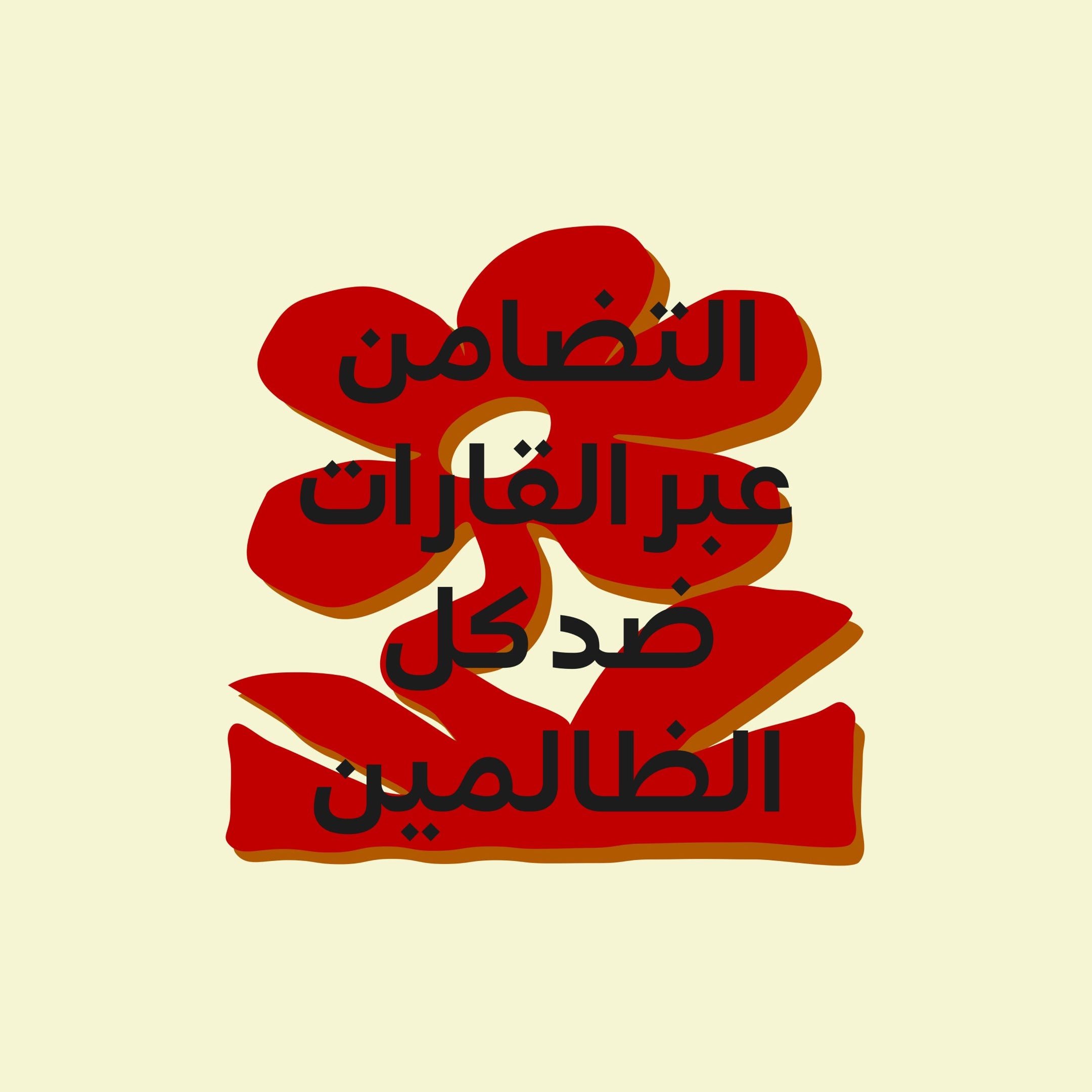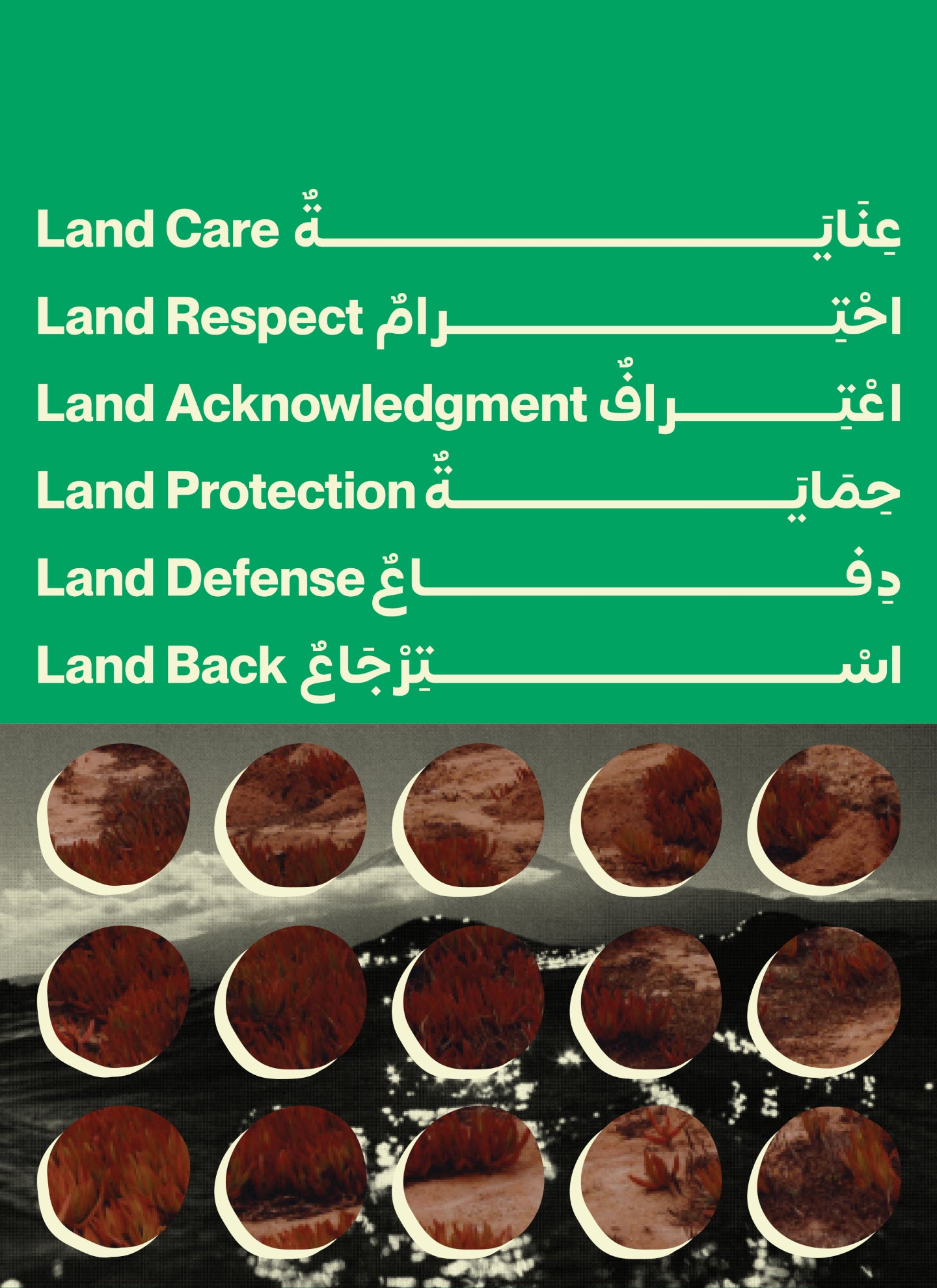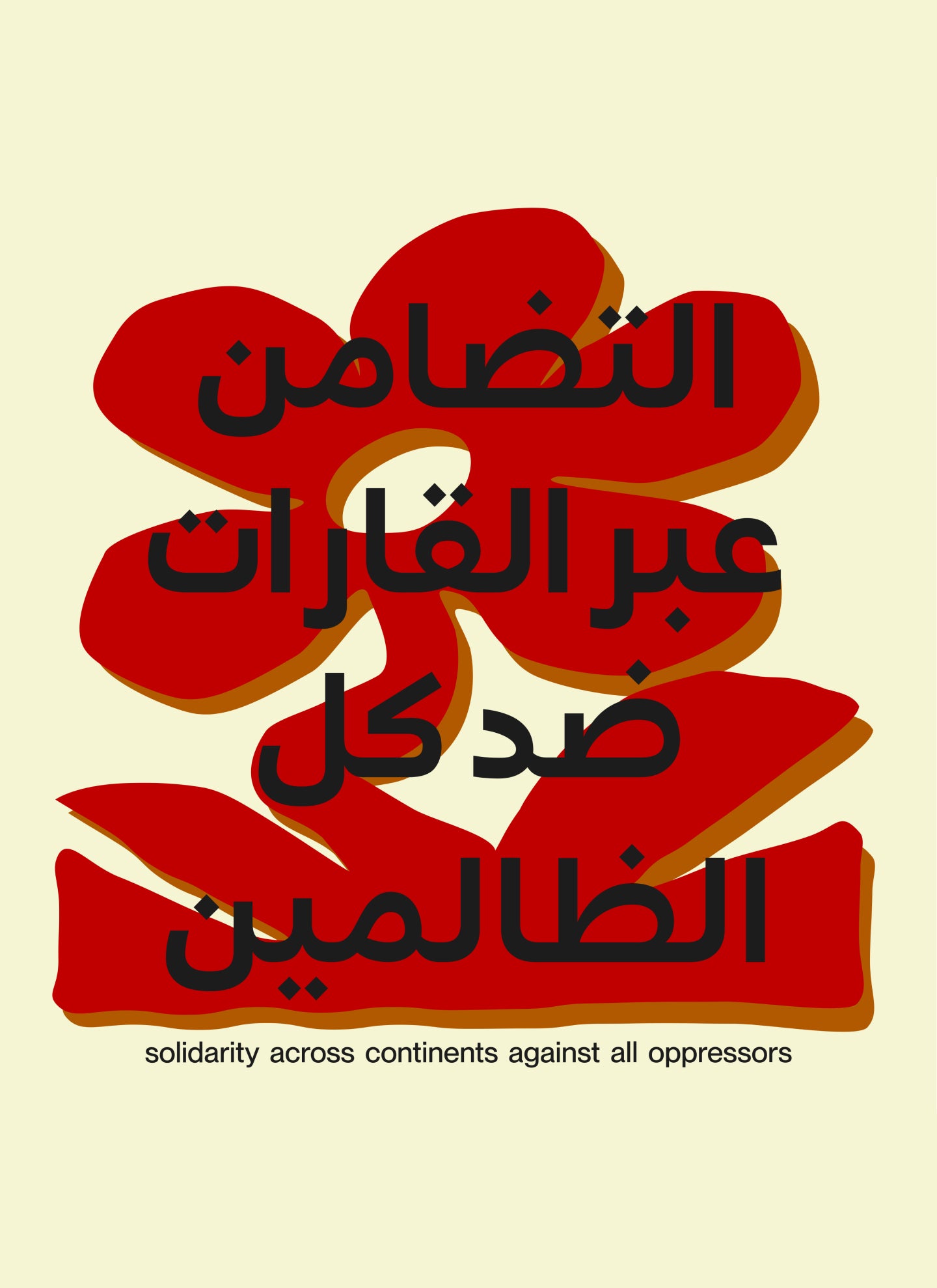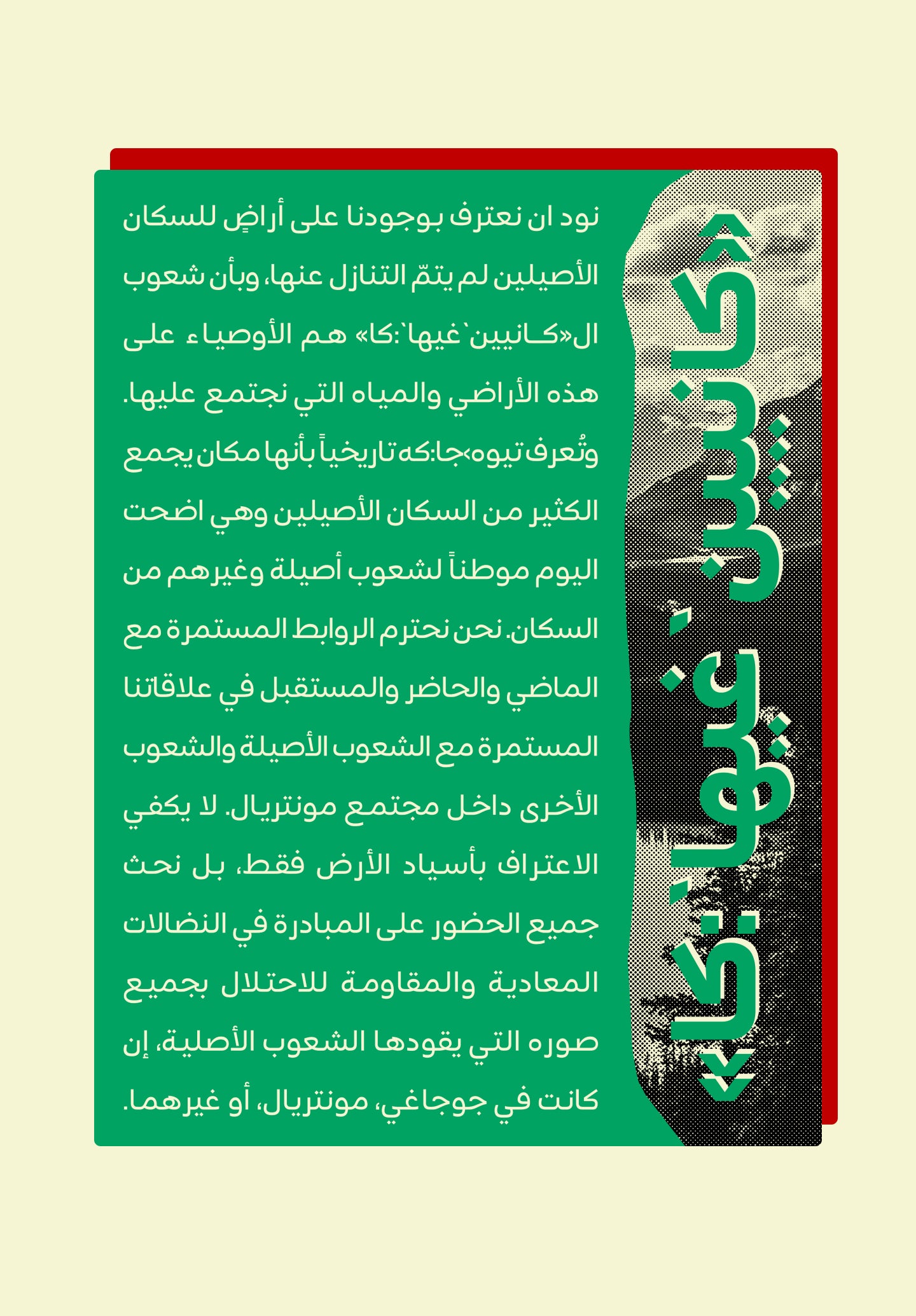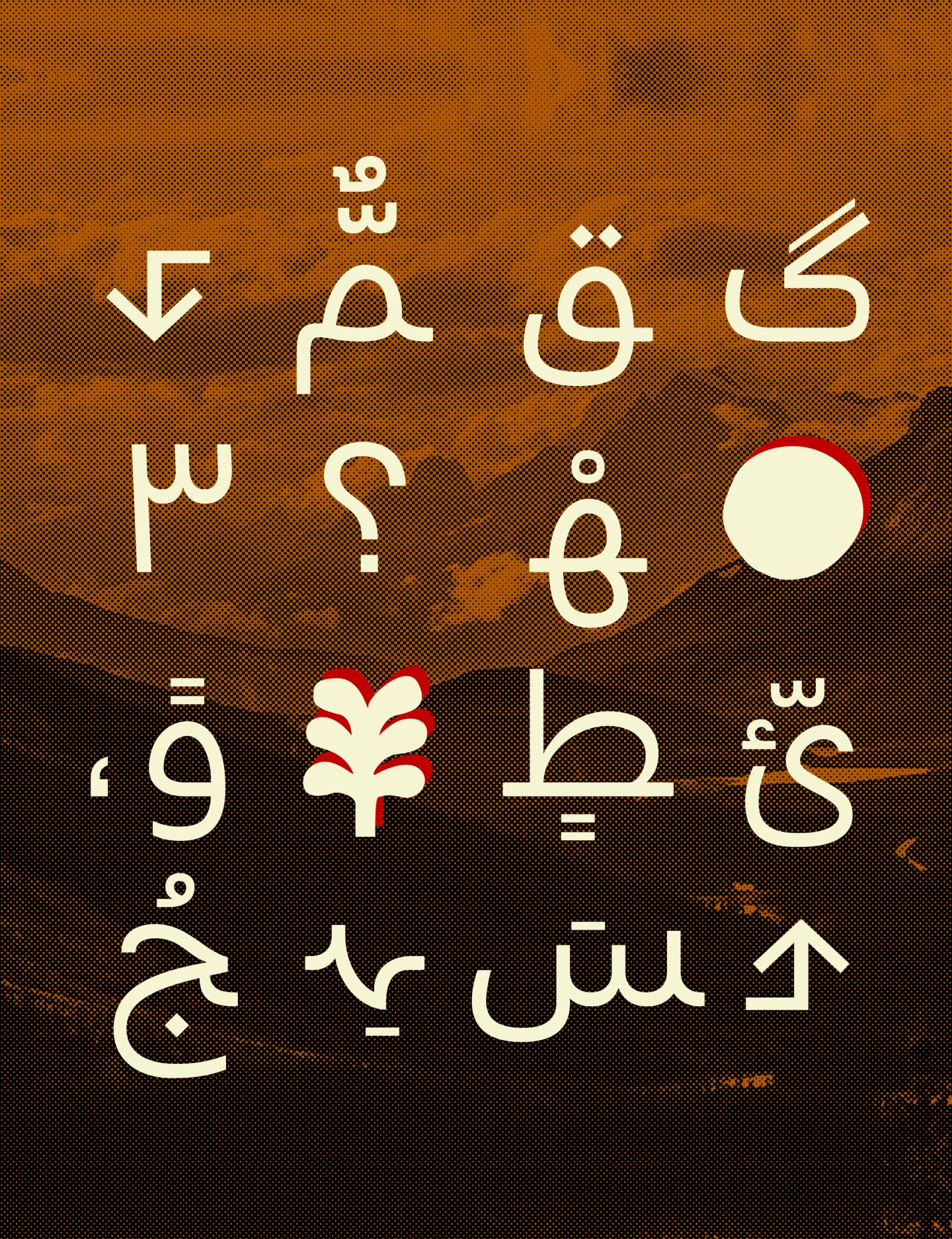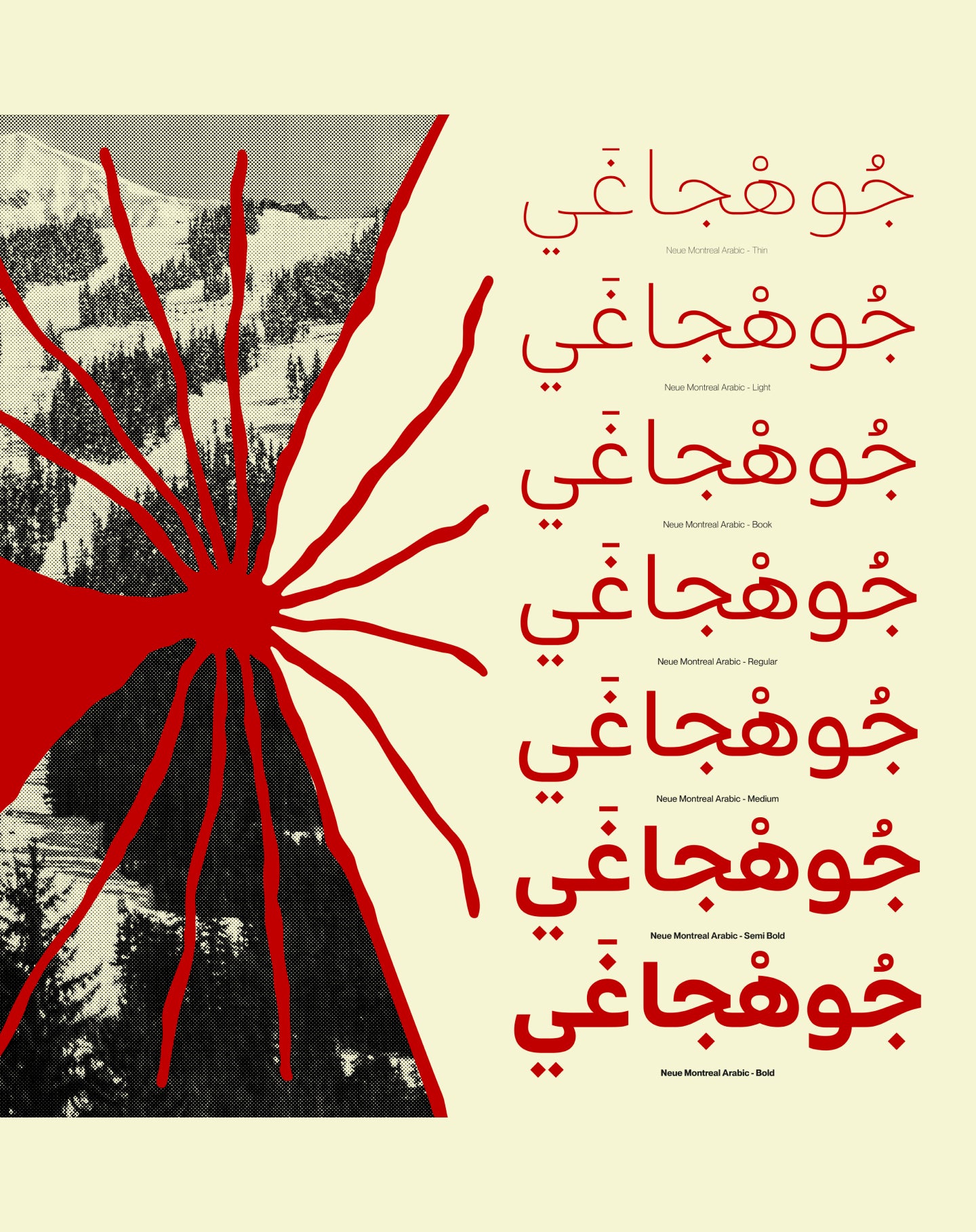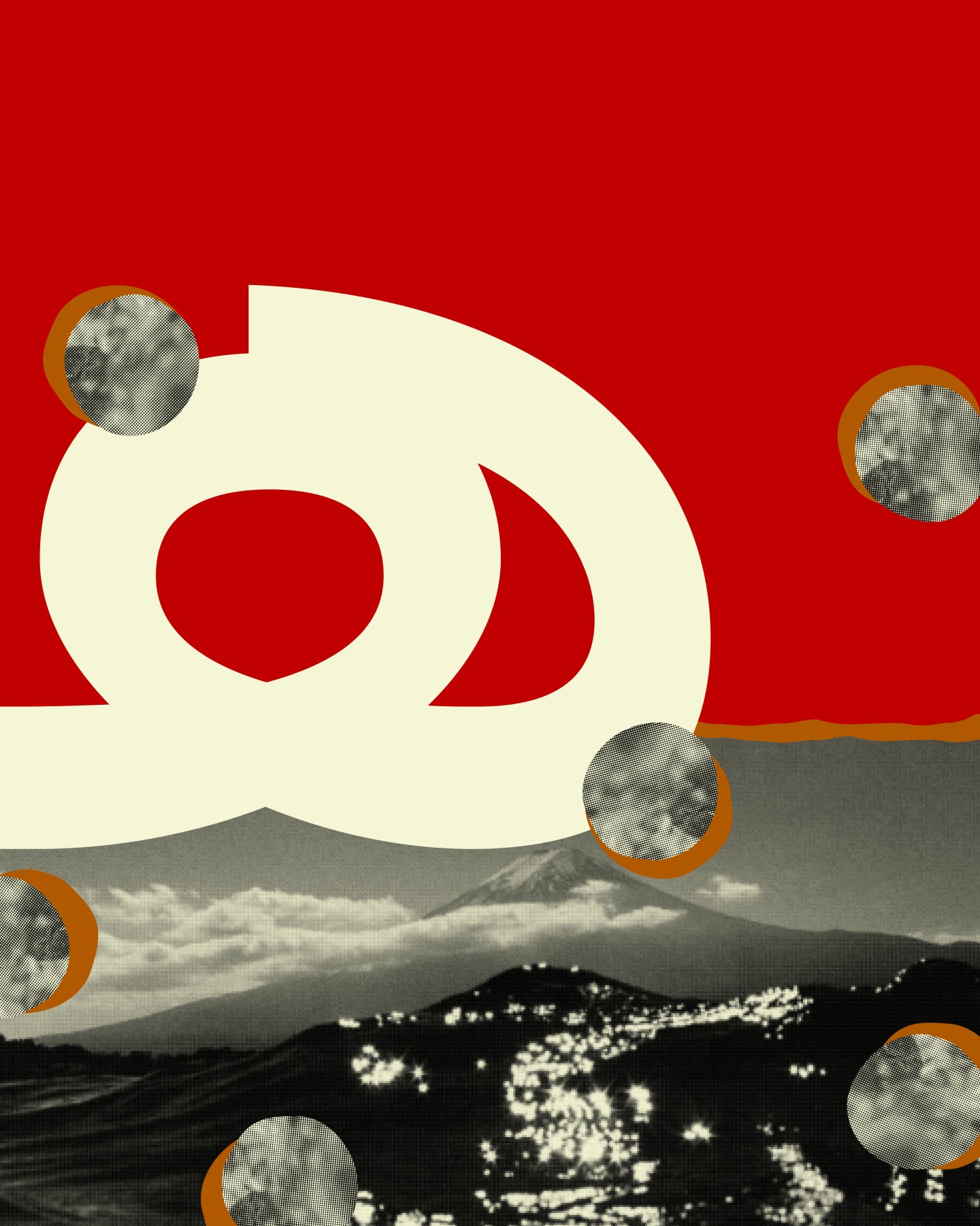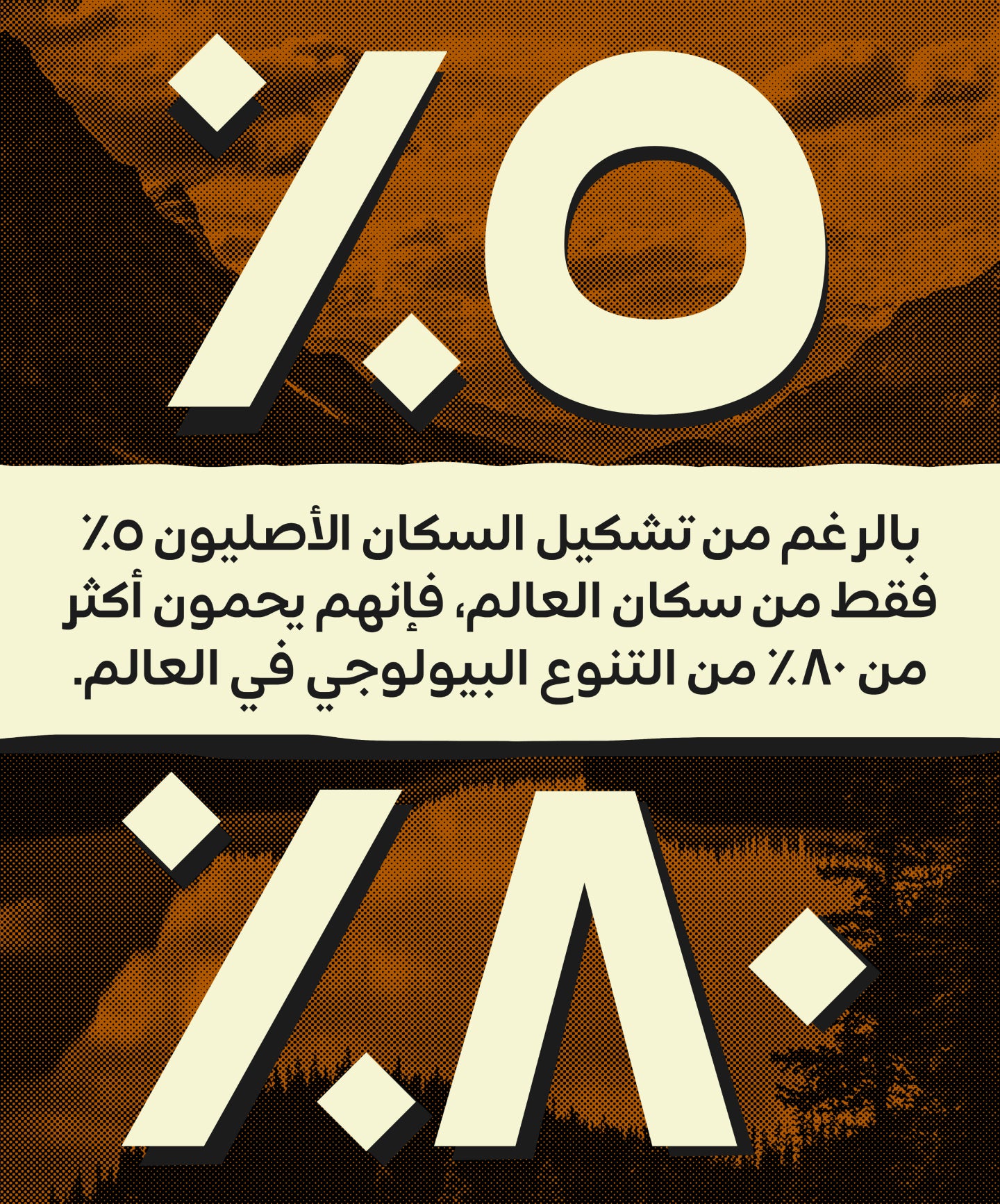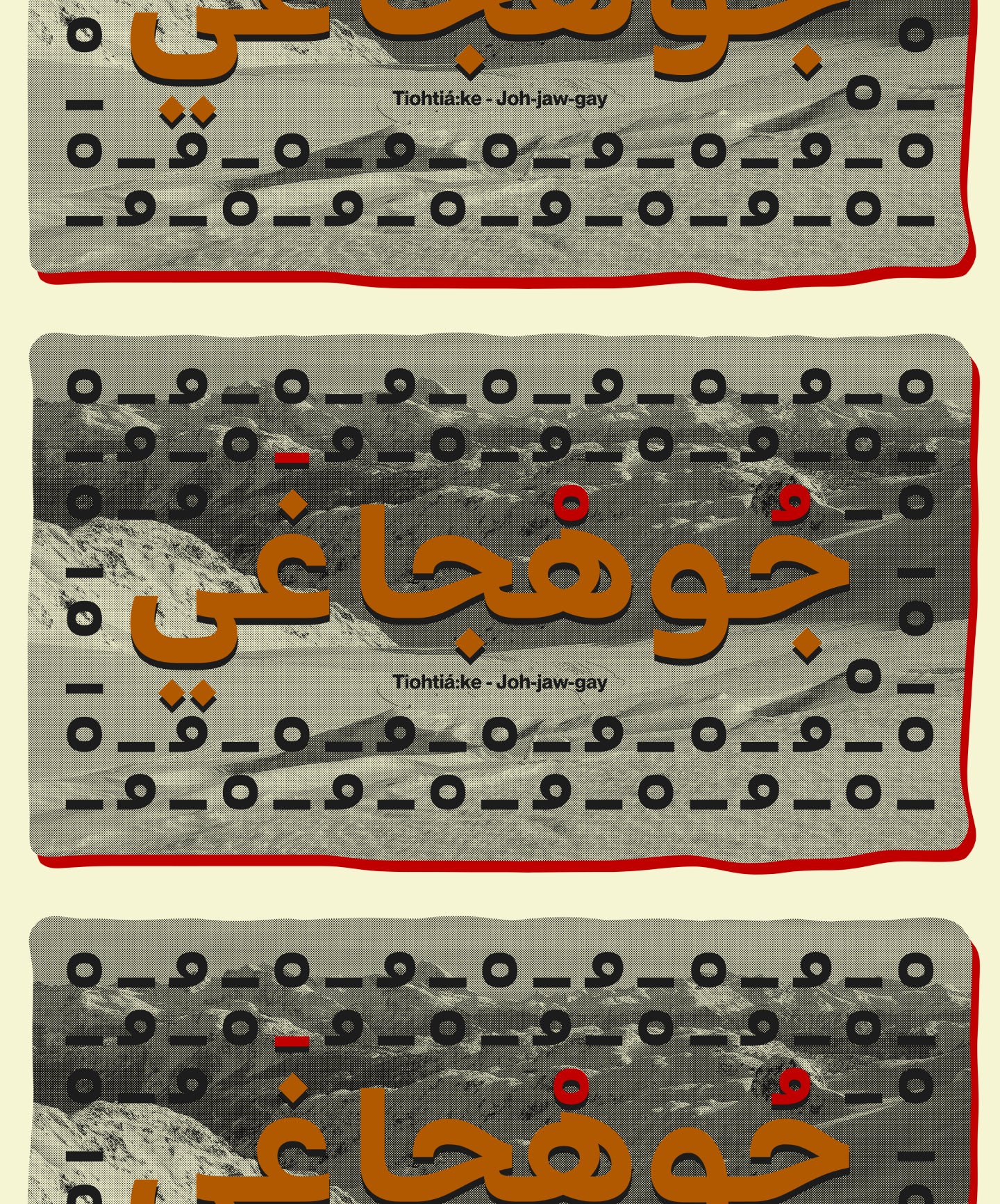
Neue Montreal Arabic
الحد الأدنى من الشكل. أقصى قدر من التناغم.
Neue Montreal Arabic
غرابة عربية حديثة تم بناؤها لتكمل نفسها وتقف على قدميها.
Neue Montreal Arabic
خط "نوي مونتريال العربي" هو خط عربي معاصر مصمم لإضفاء تناغم بصري على التصميمات متعددة اللغات. صُمم ليكون الرفيق العربي لخط "نوي مونتريال" الشهير، ويحافظ على روح الخط العربي العصري - نظيف، محايد، وعملي للغاية - مع احترام إيقاع الخط العربي ومنطقه الشكلي.
Neue Montreal Arabic
بخلاف العديد من الامتدادات العربية التي تبدو ثانوية، طُوّر خط Neue Montreal Arabic بعناية واهتمام متساويين. من العناوين الرئيسية إلى النصوص المصغرة، يحافظ الخط على هيكل متناسق، ونسب متوازنة، وسهولة قراءة ممتازة، مما يجعله مثاليًا لهويات العلامات التجارية، وواجهات الويب، والمحتوى التحريري، والتواصل بين الثقافات. مع التركيز الدقيق على محاذاة خط الأساس، ومطابقة الوزن، والنغمة المطبعية، يتيح خط Neue Montreal Arabic للمصممين ابتكار تجارب عربية لاتينية سلسة. سواء استُخدم جنبًا إلى جنب مع النص الأصلي اللاتيني أو كان قائمًا بثقة، فإنه يؤدي عمله بدقة هادئة وقوة متعددة الاستخدامات. متوفر بأوزان متعددة ومُحسّن للطباعة والشاشة، Neue Montreal Arabic هو أكثر من مجرد ترجمة - إنه جسر طباعي. مصمم لأنظمة التصميم التي تُقدّر الوضوح والترابط والتفكير التصميمي المعاصر عبر اللغات.
Neue Montreal Arabic is variable
Neue Montreal Arabic's Features
Alternate a
Round dots
Standard ligatures
Minimal form. Maximum harmony.
Welcome to the Arabic version of our most popular typeface, Neue Montreal. A versatile Grotesque font with the spirit of a display font. Complete with 7 weights also including Cyrillic support. This typeface was created to be your next champion font.
This timeless Sans was inspired by what makes Montreal the great design city it is today, from the Expo 67 to its contemporary effervescent design scene. It has been used by many global and local brands.